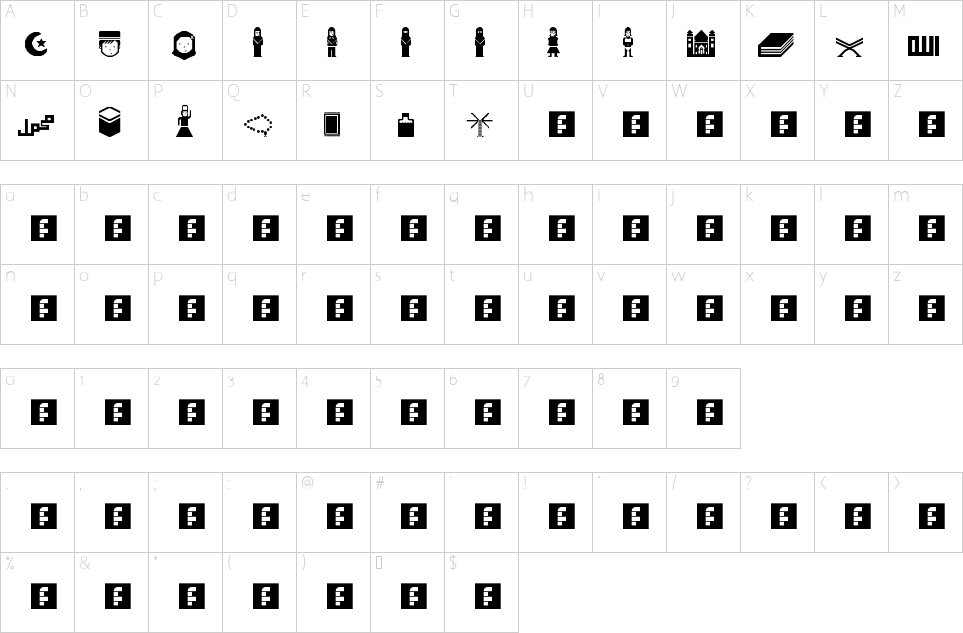
Descubra a cultura islâmica através das letras com DBA Muslim Font. Esta elegante e profunda fonte foi criada por Adien Gunarta, oferecendo um visual único para escritas árabicas e muçulmanas. Com sua design cuidadosamente elaborado, DBA Muslim font é perfeita para ambientes de mídia social islâmica, revistas ou blogs que celebram as raízes culturais desses grupos. Se você está procurando por uma maneira criativa de mostrar respeito e apreciar a cultura islâmica através da linguagem visual, DBA Muslim font é um ótimo escolha para tornar sua mensagem mais compreensível e interessante para todos os que desejam aprender mais sobre o Islã. Seu design único foi projetado para ser utilizado em sites web ou dispositivos móveis sem perda de qualidade, garantindo uma experiência visual única e envolvente para quem a usa. Com sua facilidade na integração para designers gráficos, DBA Muslim font se torna um recurso valioso para qualquer projeto que deseja celebrar as belas raízes culturais da cultura islâmica.